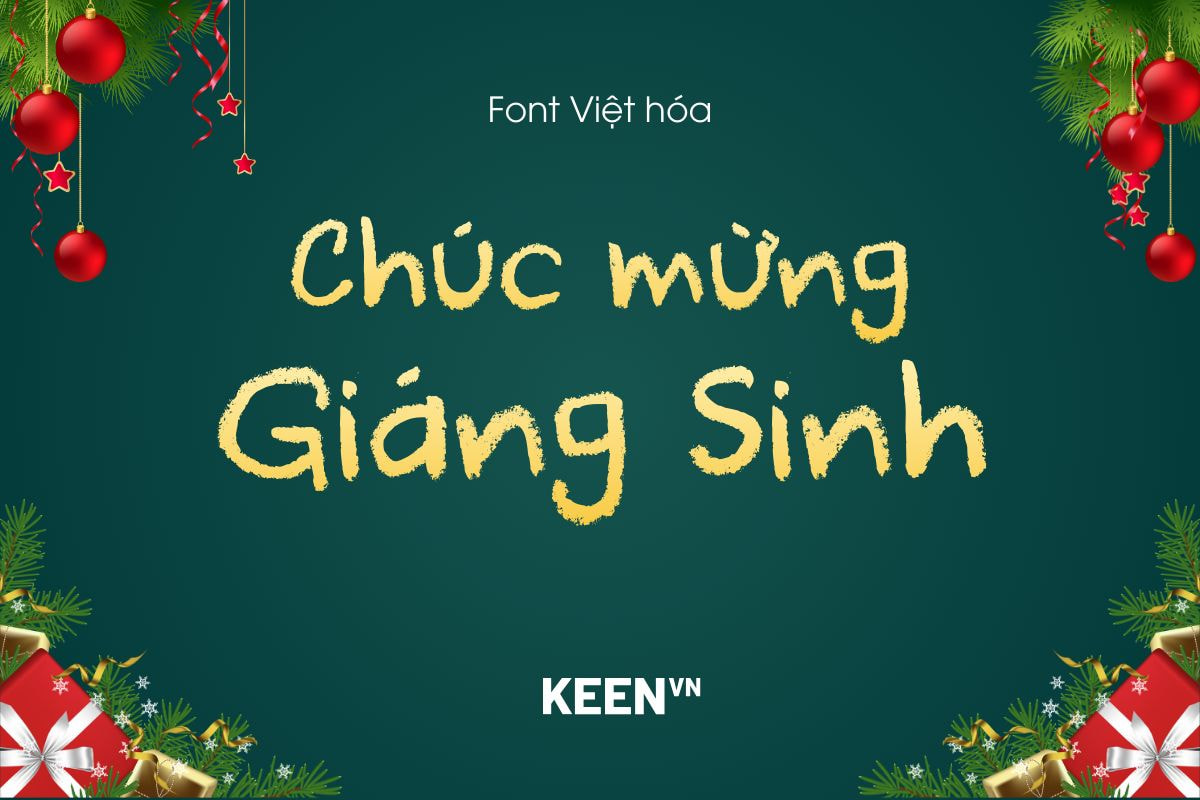
Font Việt hóa FC DK Cool Crayon
- Hỗ trợ đầy đủ dấu tiếng Việt
Font Việt hóa FC DK Cool Crayon mang đến cảm giác thân thiện và ấm áp ngay từ những nét chữ đầu tiên, như những đường phấn bảng được vẽ đầy ngẫu hứng nhưng vẫn mềm mại và tự nhiên. Được thiết kế bởi David Kerkhoff, font chữ này mô phỏng chân thực phong cách viết phấn, tạo nên vẻ gần gũi rất đặc trưng — điều khiến nó trở thành lựa chọn tuyệt vời cho các ấn phẩm hướng đến sự vui tươi, sáng tạo và mang màu sắc trẻ thơ. Phiên bản Việt hóa do Font Chuẩn thực hiện giúp người dùng dễ dàng ứng dụng trọn vẹn trong các thiết kế tiếng Việt, mở rộng khả năng khai thác trong nhiều dự án khác nhau.
DK Cool Crayon đặc biệt phù hợp với các thiết kế dành cho giáo dục như thiệp chúc mừng Ngày Nhà giáo Việt Nam, poster trường học, bảng thông báo, bìa tài liệu hay các ấn phẩm dành cho trẻ em. Các đường nét mang hơi hướng thư pháp phấn bảng giúp font vừa tinh nghịch, vừa nghệ thuật, tạo nên cảm giác thân thiện và truyền cảm hứng. Không chỉ dừng lại ở đó, font còn mang không khí lễ hội ấm áp, phù hợp để dùng trong thiệp Giáng Sinh, banner mùa đông hay các thiết kế truyền thông trong mùa lễ cuối năm.
Cấu trúc chữ của FC DK Cool Crayon được thiết kế cân đối, từng ký tự như được vẽ thủ công để đảm bảo tính tự nhiên nhưng vẫn rõ ràng, dễ đọc. Nhờ hỗ trợ đa ngôn ngữ và bộ ký tự đầy đủ, font có thể sử dụng linh hoạt trong thiết kế tiêu đề, bao bì sản phẩm, truyền thông sự kiện hay các dự án sáng tạo cần hơi thở gần gũi. Nếu bạn đang tìm một kiểu chữ mang lại sự ấm cúng, thân thiện và đậm chất thủ công, FC DK Cool Crayon chắc chắn sẽ là lựa chọn khiến thiết kế của bạn trở nên nổi bật và đầy cảm xúc.